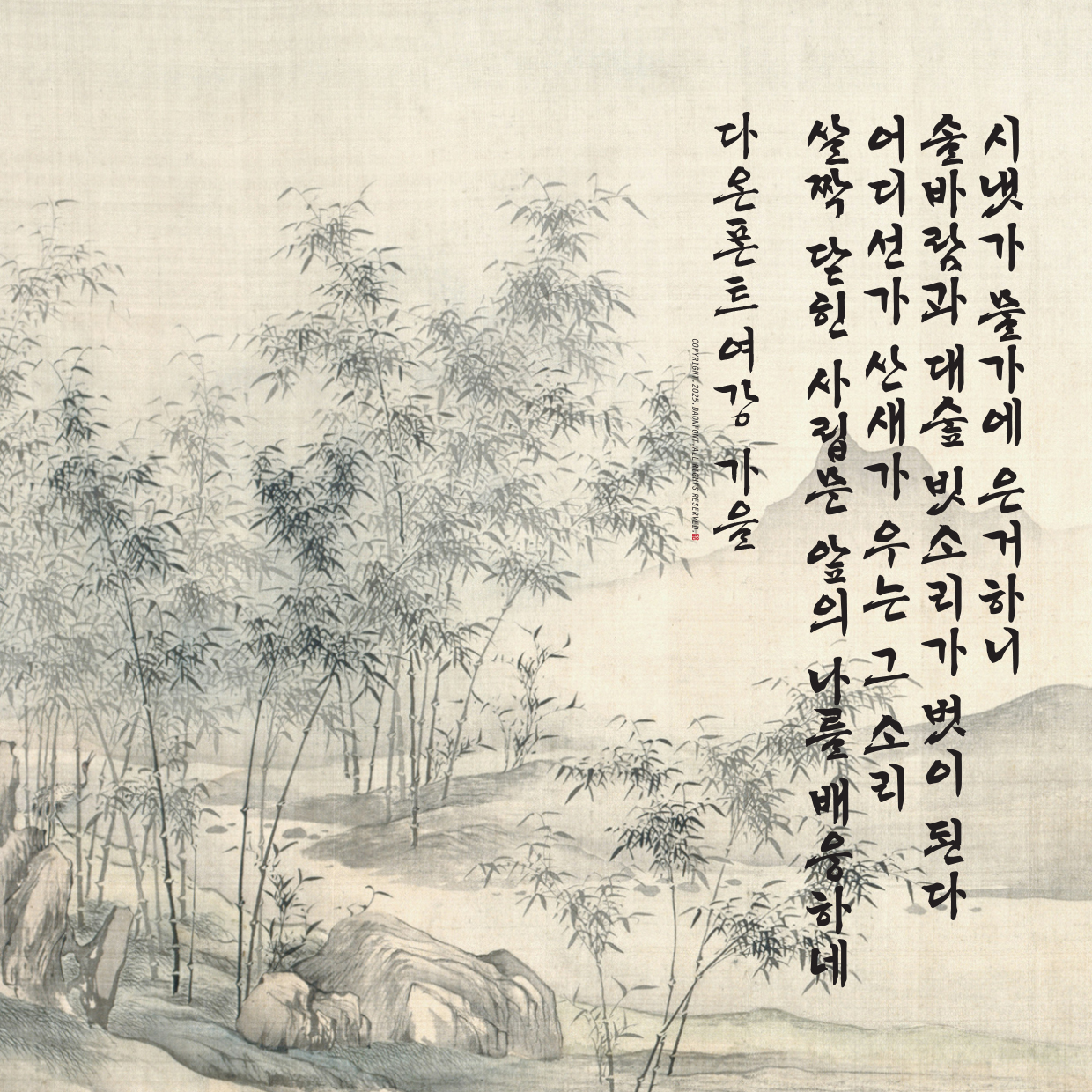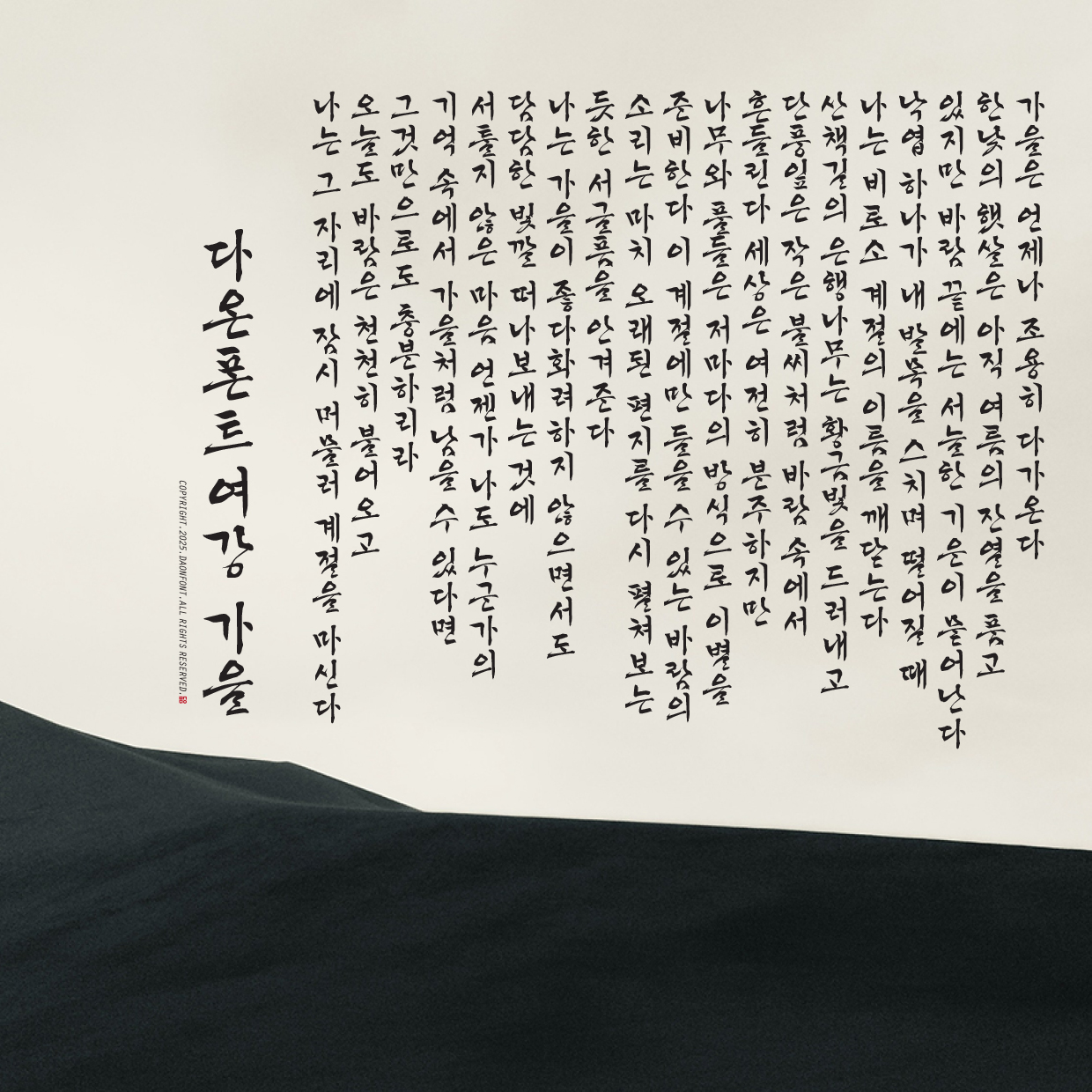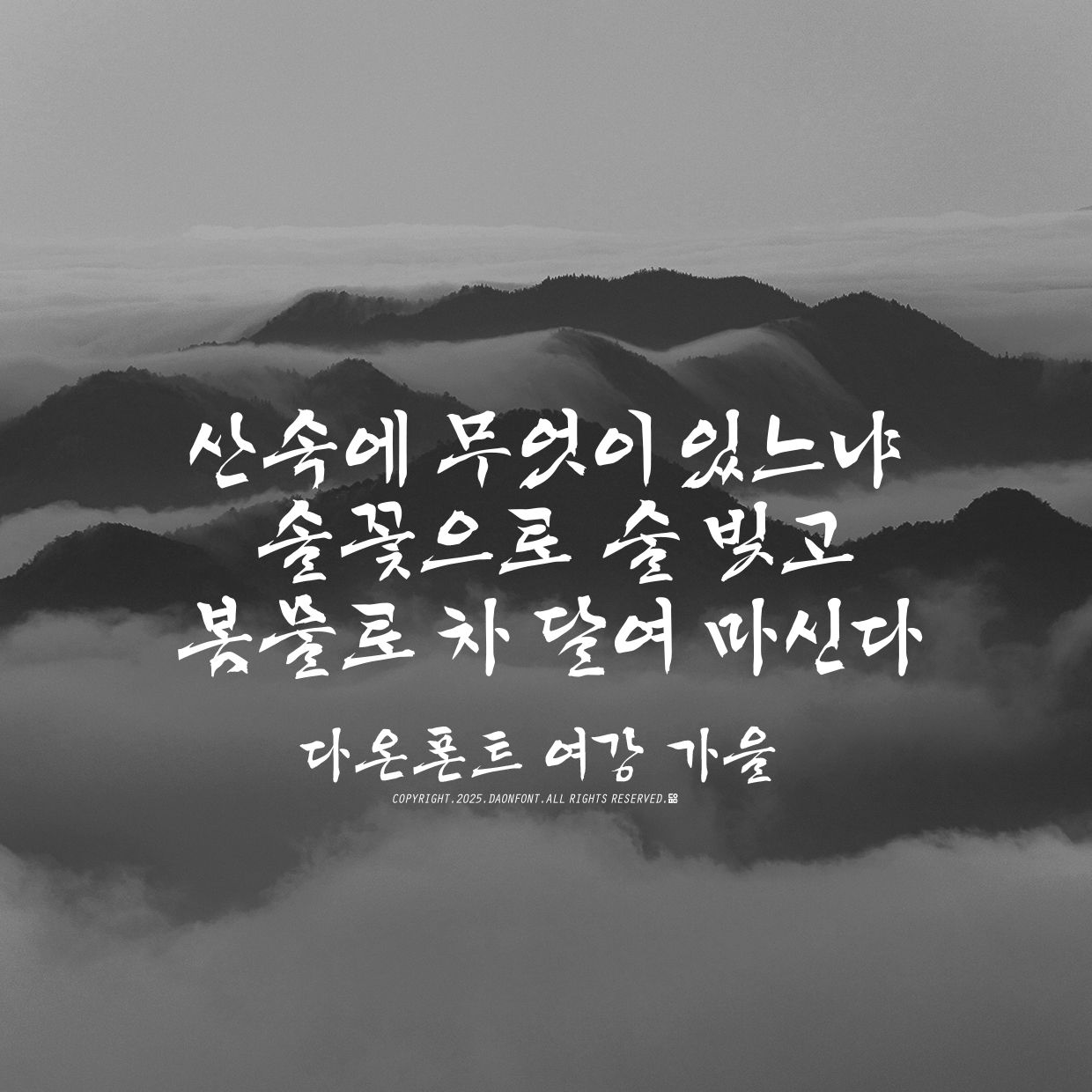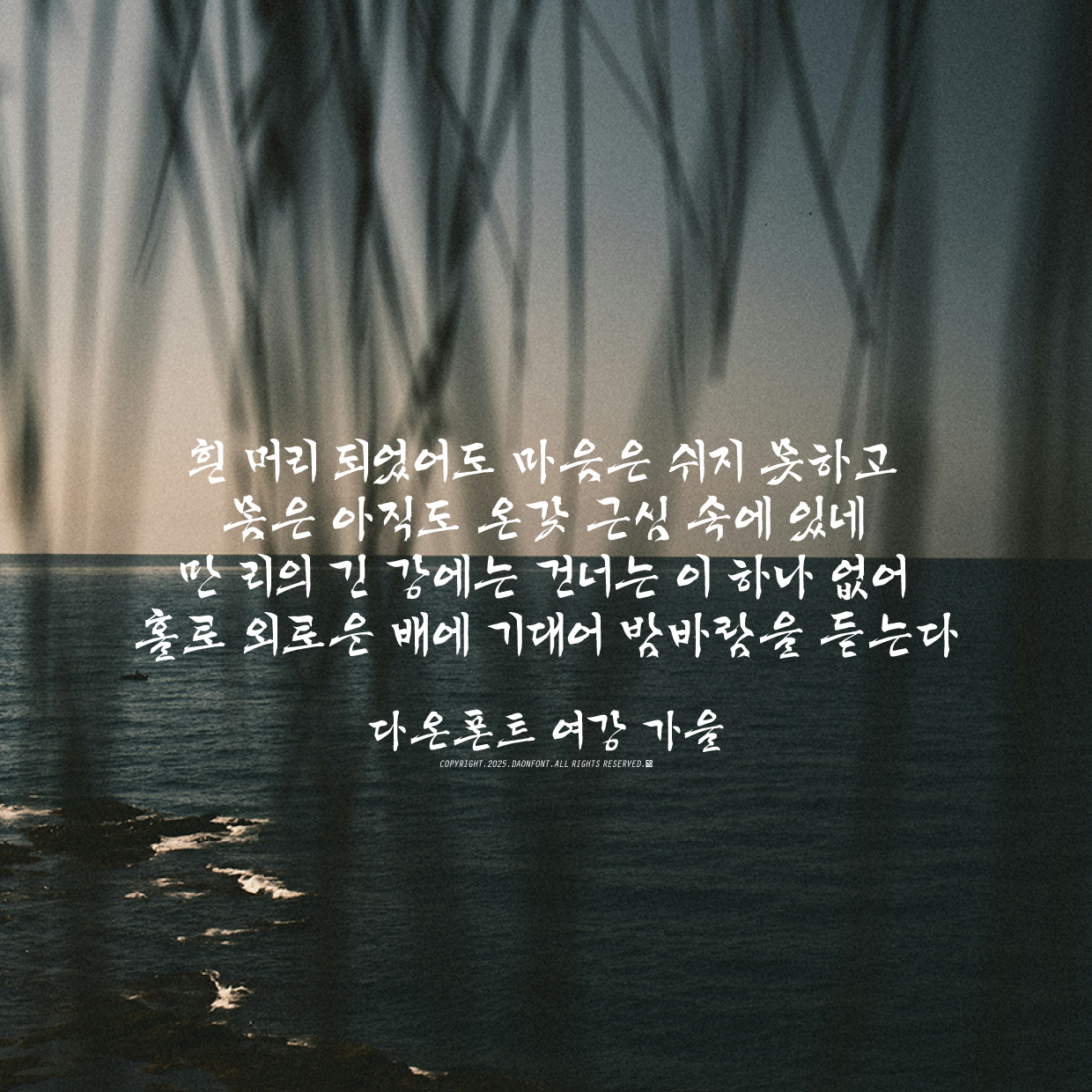
여강가을체 초벌 결과물을 먼저 여러분께 보여드립니다.
가을은 풍경이 아니라, 마음에 스며드는 계절입니다.
다온폰트 여강 가을체는 전통 붓결 속에 담긴 계절의 온기를
글자로 옮겨 담았습니다. 읽는 순간, 마음에 가을이 머뭅니다~
오늘, 드디어 여강가을체 초벌 작업이 끝났습니다.
따끈한 초벌 결과물을 먼저 여러분께 보여드립니다.
곧 다듬어질 최종본에서는
더 깊은 가을의 향기와 묵직한 울림을 느끼실 수 있을 거예요.